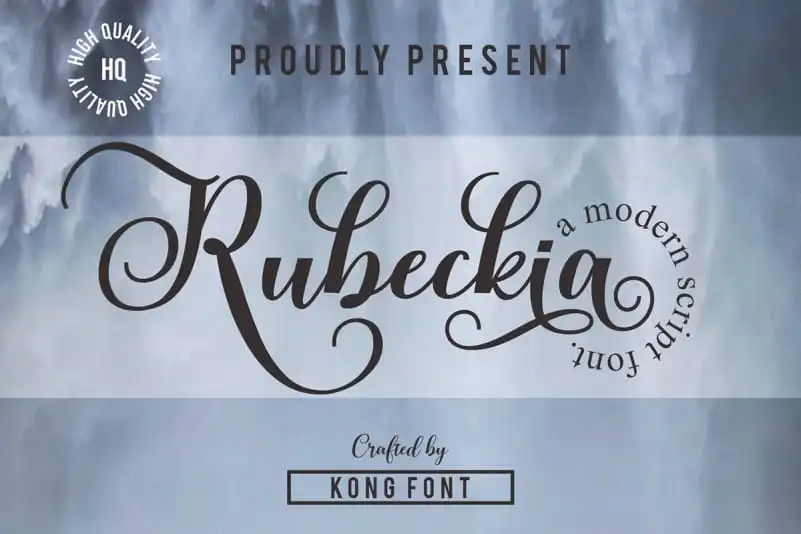
Rubeckia Calligraphy Font – Download Grátis
Aqui está uma versão curta e envolvente da descrição para a página de download da font ‘Rubeckia Calligraphy Font’: Descubra agora a Rubeckia, uma nova fonte de calligrafia script que incorpora linhas suaves, fluidez elegante e alternativas encantadoras. Esta fonte foi criada por fontkong para quem aprecia a sofisticação da calligrafia em formatos digitais. Rapstomer adicional inclui alternativas de letras, ligaturas e suporte internacional para as mais comuns linguagens ocidentais. Ideal tanto para uso em títulos, assinaturas, logotipos, cartas pessoais, correspondência formal, selos, mensagens, materiais publicitários, etiquetas e até mesmo em material de identificação, a Rubeckia é perfeita para quem busca um toque personalizado em suas criações. Com sua elegância única e funcionalidade versátil, a Rubeckia Calligraphy Font se torna um recurso indispensável para designers gráficos e criativos.